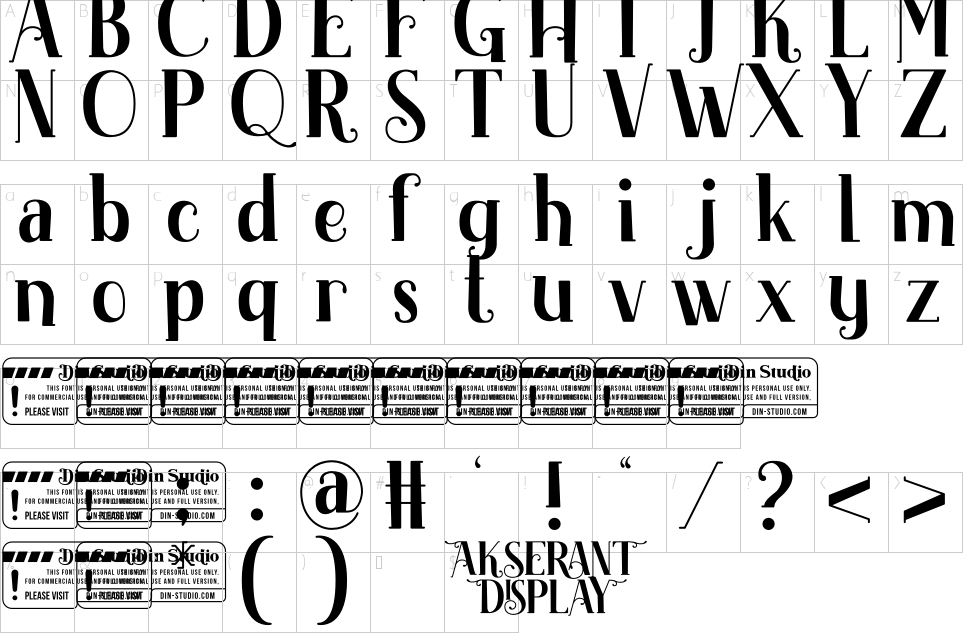
Akserant Display Font – Download Grátis
A Akserant Display é uma fonte que combina elegância e sofisticação, criada pelo Din Studio. Seu design fluido e arredondado torna-a uma escolha ideal para aplicações que valorizam uma aparência atraente e sofisticada. Esta fonte foi projetada para oferecer uma experiência de uso fluida em ambientes Windows e Mac, tornando-a uma excelente opção para designers gráficos e tipógrafos que buscam uma fonte de qualidade gratuita. Com seu design moderno, a Akserant Display pode ser usada em variados ambientes, seja em sites, apps ou impressões digitais, tornando-a uma fonte versátil e atraente. Seu design suave e equilibrado, além de sua facilidade de uso, a tornam uma escolha popular, sendo baixada pelo número incrivelmente alto de 1.070 vezes. Instale a Akserant Display agora e faça seu design brilhar.